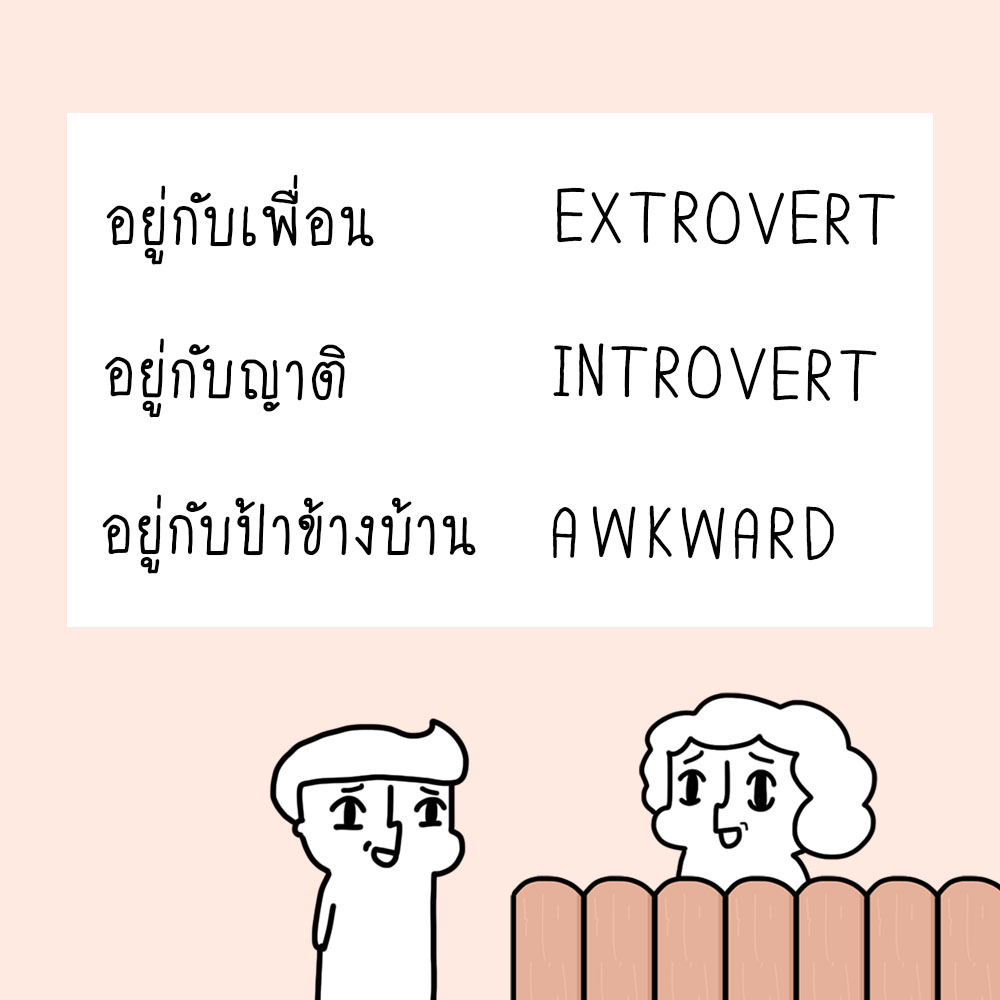
‘นัดเป็ด’ เพจการ์ตูน Gag ลายเส้นน่ารักสุดกวน เปิดตัว ‘ฟอนต์ลายมือนัดเป็ด’ ของตัวเองแบบเดียวกับที่ใช้ในเพจให้ทุกคนสามารถซื้อไปใช้ทั้งภาษาไทยและภาษาอังกฤษ รวมถึงเลือกซื้อแบบใช้ส่วนตัวหรือเชิงพาณิชย์ก็ได้